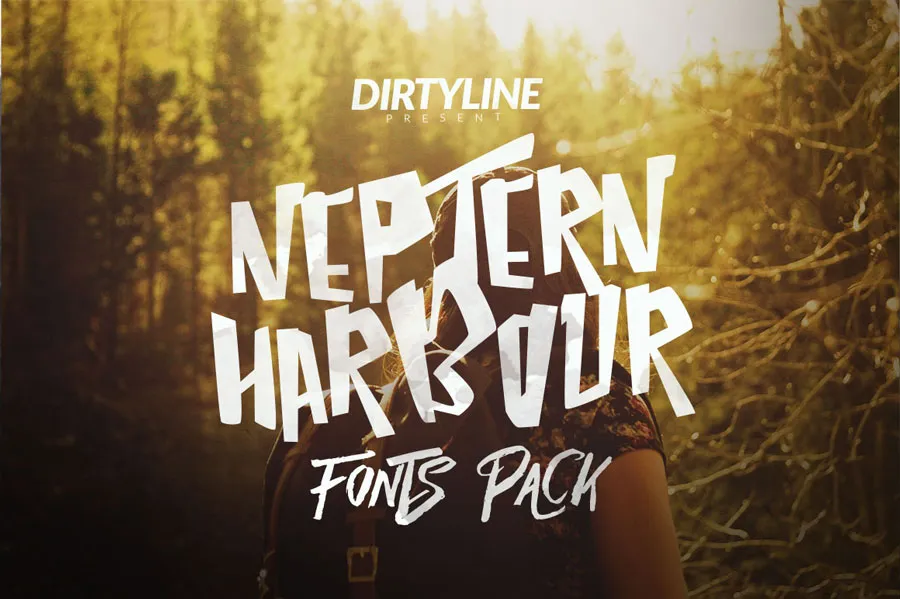
Neptern Harbour Font – Download Grátis
A Neptern Harbour é uma fonte de estilo handrawn projetada para quem busca uma mistura única e moderna. Com sua simplicidade elegante e personalidade forte, ela foi criada especificamente para atender às necessidades de qualquer projeto design que possua uma paleta visual interessante. A fonte pode ser usada em uma variedade de aplicações, incluindo títulos, assinaturas, logotipos, correspondências, cartas-civilizadas, identificações de viagens, folhas de papel, panfletos, selos, adesivos e muito mais. Como um designer cuidadoso da fonte Neptern Harbour, Hamilton criou uma fonte que pode brilhar em qualquer projeto que você estiver desenvolvendo. Sua elegância moderna e personalidade inovadora tornam-se perfeitas para atração de olhares e criação de design único.